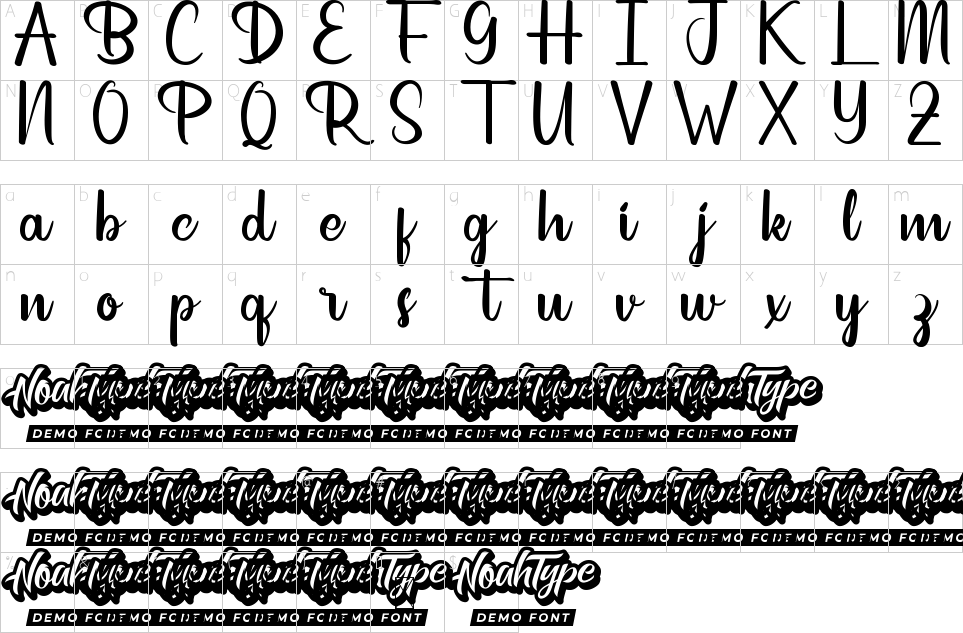
A Dillsburg City Font é uma elegante escolha para designers que buscam um estilo urbano mas ao mesmo tempo sofisticado. Desenvolvida por noahtype, esta fonte pode ser facilmente integrada tanto no Windows quanto no Mac. Com seu design cuidadosamente pensado e sua simplicidade, a Dillsburg City oferece uma abordagem moderna que se destaca em qualquer layout editorial ou criação digital. Embora não seja exatamente conhecida por ter características únicas, a Dillsburg City mantém um padrão consistente de qualidade. Descobriu o seu próprio estilo? Experimente esta fonte e veja como ela se adaptaria ao seu projeto. Download gratuito da Dillsburg City Font para Windows e Mac é uma ótima maneira de começar sua pesquisa por fontes gráficas de alta qualidade sem custos.